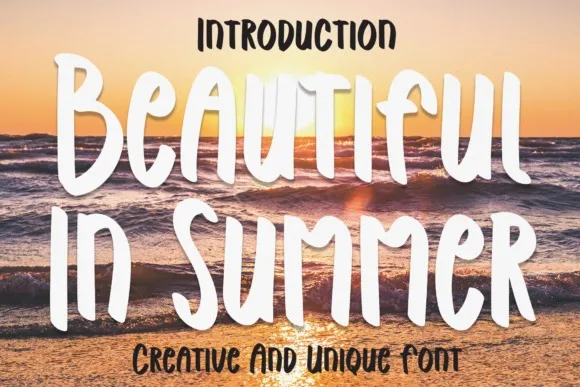
Beautiful In Summer Font – Fonte Grátis
Beautiful In Summer Font
Esta é uma fonte de exibição simples e informal. Com adaptação a vários ideias de design, essa fonte impressionará com seu visual divertido e amigável. Ela será perfeita para adicionar um toque único e divertido aos seus projetos de arquitetura digital ou impressão. A fonte “Beautiful In Summer Font” foi criada pelo designer andikastudio, uma escolha ideal se você está procurando por uma opção elegante e versátil para dar um toque especial em qualquer design que desejar. Experimente essa fonte no seu próximo projeto e veja o impacto único que ela pode ter em seus trabalhos de design.